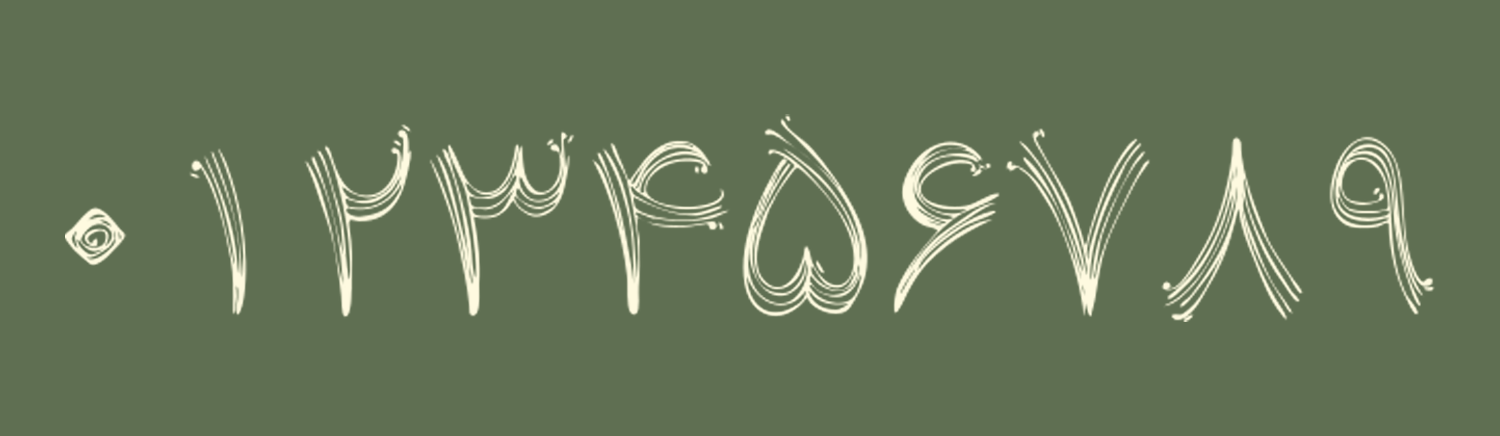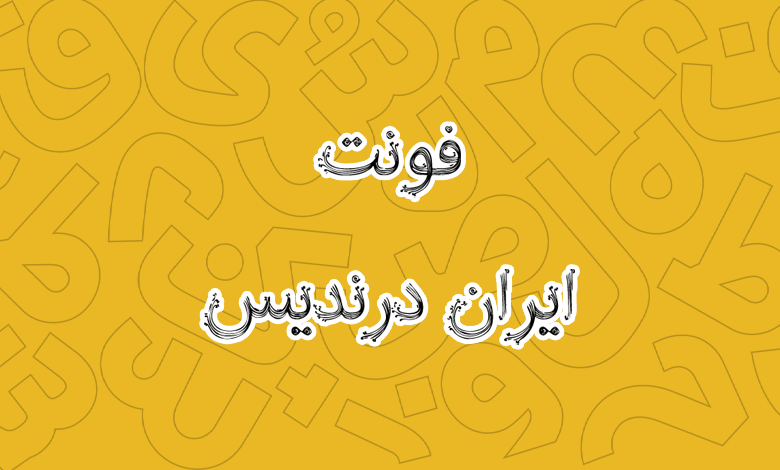
فونت ایران درندیس (Iran-Dorandis)
فونت ایران درندیس (به انگلیسی: Iran-Dorandis) در گروه فونت رایگان و فانتزی است طبقهبندی میشود که با توجه به نوع طراحی و الهام از طبیعت برای کارهای گرافیکی و تبلیغاتی مناسب است.
سنا میلانی این قلم را با الهام از طبیعت طراحی کرده که دارای ساختار اینلاین و خطی است که نمونه آن را پیش از این در قلمهایی نظیر فونت کاموا و فونت ارژن دیده ایم. اما با این تفاوت که انتهای حروف به طرههایی از گیاهها تزئین شده است؛ گویی حروف در حال جوانه زدن و رشد کردن هستند.
در ادامه این نوشته از سایت فونتچی به نقد و بررسی فونت رایگان ایران درندیس خواهیم پرداخت؛ فونتی با وزن معمولی که میتوانید در ابعادی با اندازه بزرگ در کارهای گرافیکی تبلیغاتی از آن استفاده کنید یا اینکه در صنعت چاپ، برای جلد کتب و مجلاتی که در حوزه کودک یا محصولات ارگونومیک هستند از آن بهره ببرید.
فونت ایران درندیس را میتوان یک قلم فانتزی عالی برای کارهایی که جنبه تزئینی و گرافیکی دارند در نظر گرفت. این قلم با تلفیقی از چند ساختار مختلف سنس، اینلاین، فانتزی و تزئینی که در خود دارد ارتباطی کاملا صمیمی، نرم و دوستانه را با مخاطب ایجاد میکند.
در اندازههای بزرگ به دلیل ساختار اینلاین و داشتن طرههای تزئینی که الهام گرفته از طبیعت است نیز خود را بهتر نشان خواهد داد که همین موضوع آن را به انتخابی عالی برای کارهای تبلیغاتی بدل کرده است.
سبک طراحی و وزن فونت ایران درندیس
تمامی حروف در فونت ایران درندیس با الهام از تزئینات گیاهی ابتدا روی کاغذ و با دست طراحی شدهاند که نسخهای الهام گرفته شده از قلم ایران معمولی هستند. با ایجاد تغییرات جزئی بر روی این قلم و افزودن طرههای تزئینی گیاهی و مهمتر از آن ایجاد ساختار اینلاین در این قلم، نهایتا ایران درندیس خلق شد.
پشتیبانی از زبان فارسی و عربی
فونت ایران درندیس فارسی به لطف رسم خط فارسی برای سایر زبانها نظیر عربی و کردی که مبتنی بر این زبان هستند نیز قابل استفاده است. اما ساختار این قلم در این زبانها طوری نیست که همه حروف را شامل شود. حروفی مثل «ک، ی، ه، ؤ، ئ» که در تصویر زیر هم از آنها استفاده شده، فاقد نسخه عربی بوده و کاراکترهای «دو نقطه، همزه» که در بالا یا پایین حروف در عربی درج میشود را شامل نمیشود.
تمامی حروف برای این قلم فارسی در نظر گرفته شده است که پشتیبانی کاملی برای زبان فارسی دارد. اما در سایر زبانها صرفا حروف مشترکی که فارسی هستند تایپ خواهد شد و شکل متفاوت حروف برای زبانهای عربی یا اردو مثل حروف «ﮧ، ﮩ، ے» دارای گلیف اختصاصی نیست.
دارای اعداد فارسی استاندارد
در بخش اعداد نیز این قلم از اعداد استاندارد فارسی پشتیبانی میکند. صفحه کلید شما روی هر زبان خاورمیانهای مانند فارسی، عربی، کردی یا اردو که قرار داشته باشد اعداد به صورت زیر تایپ خواهند شد.
مانند حروف عربی برای اعداد هم خبری از گلیف اختصاصی برای اعداد «۴۵۶» نیست و تمامی اعداد برای این زبانها نیز بر اساس اعداد فارسی تایپ میشوند.
مناسب تبلیغات و کارهای گرافیکی
فونت ایران درندیس مناسب تبلیغات است و با توجه به ساختار فانتزی که دارد، میتوانید از این قلم در کارهای گرافیکی که تلفیقی از حوزه سلامت، محصولات گشاورزی، ارگانیک و طبیعی هستند بهترین بهرهوری را از آن ببرید.
کاربرد دیگر این قلم میتواند در حوزه چاپ و تبلیغات باشد. میتوانید جلد کتب و مجلات را با استفاده از این قلم و با اندازه فونت درشت تایپ کنید که در اندازههای بزرگ نیز ظاهری عالی، نرم و صمیمی به کتاب خواهد داد. خصوصا در حوزه کتاب کودک و نوجوان که ارتباط صمیمی بیشتری را فراهم میکند.
جدیدترین نسخه فونت ایران درندیس ورژن ۱.۱ است که در آذر ۱۴۰۱ منتشر شده است. این قلم که دارای طراحی خطی بوده و از تزئین گیاهیی برخوردار است، در اندازههای درشت خود را بهتر نمایش میدهد که میتوانید در کارهای گرافیکی که جنبه تبلیغاتی؛ خصوصا در حوزه سلامت و محصولات مرتبط با آن استفاده کنید.